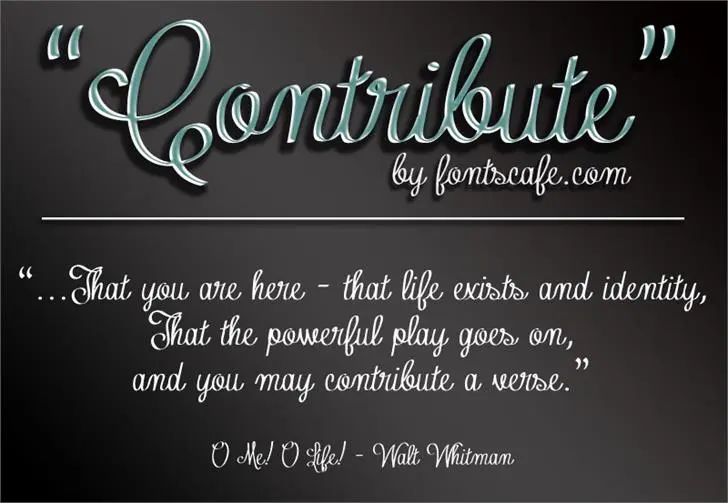
Contribute font
A fonte “Contribute” é uma escolha elegante para quem busca expressar a personalidade única em seu projeto visual. Criada em 2012 pelo Designer Hamilton, esta fonte é perfeita para designers que valorizam um estilo elegante e sofisticado. Se você está procurando por uma fonte script minimalista que se destaca, “Contribute” pode ser a sua escolha ideal. Com linhas finas e curvas fluidas, ela traz ao seu projeto uma graça e uma delicadeza incomparáveis. Ideal para cabeçalhos, nomes de empresas ou qualquer outro uso em que você deseja dar um toque especial. Esta fonte é a versão gratuita da “Contribute FREE-version”. Para obter as muitas funcionalidades e recursos disponíveis para o seu projeto profissional, pode-se adquirir a sua versão completa através do site de FontsCafe. Além disso, se você quiser acompanhar as últimas novidades dos designers desta fonte ou até mesmo sugerir ideias para futuras criações, é possível seguir a página oficial no Facebook e Twitter da FontsCafe. Experimente “Contribute” hoje e revolucione o design visual do seu projeto!